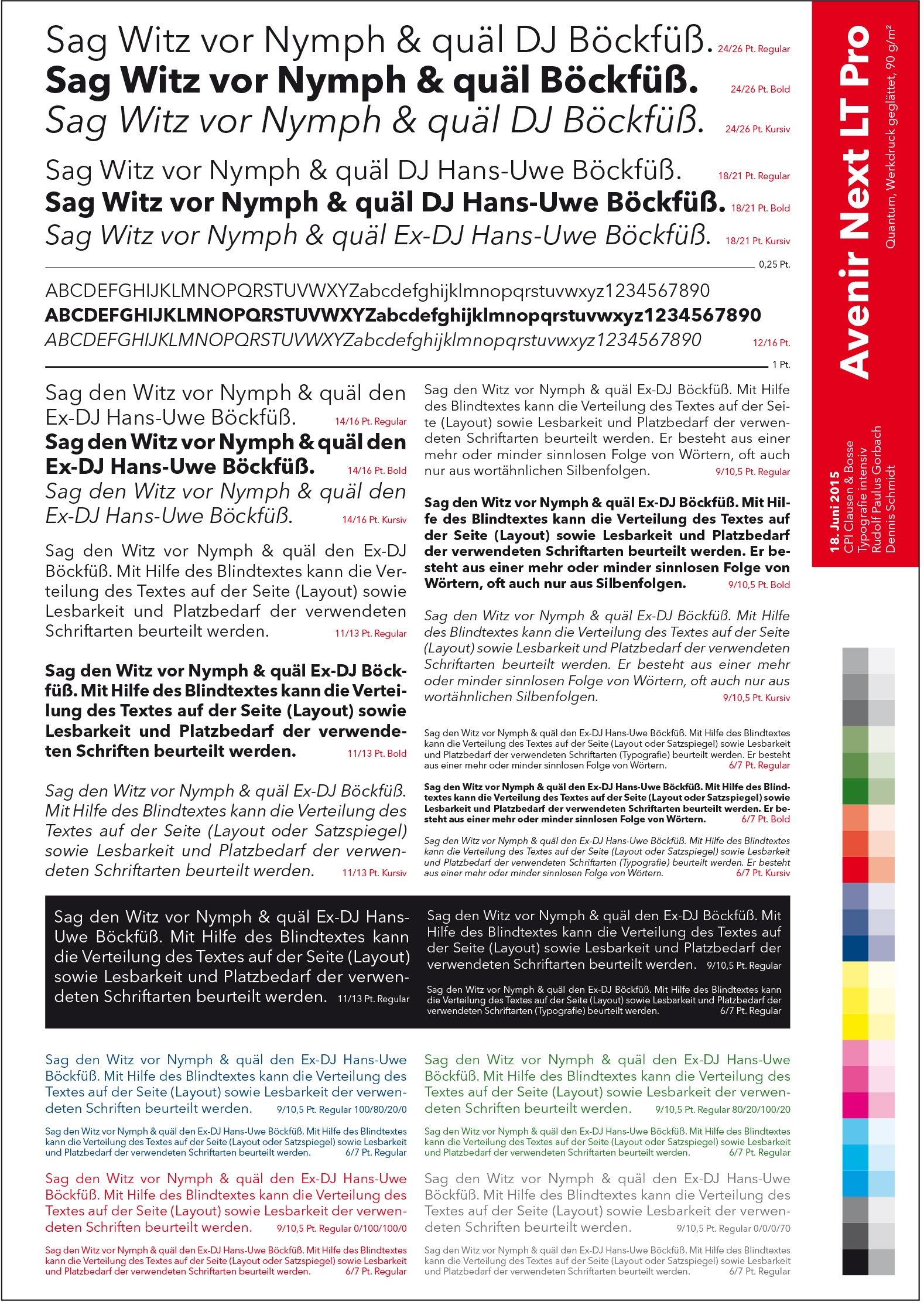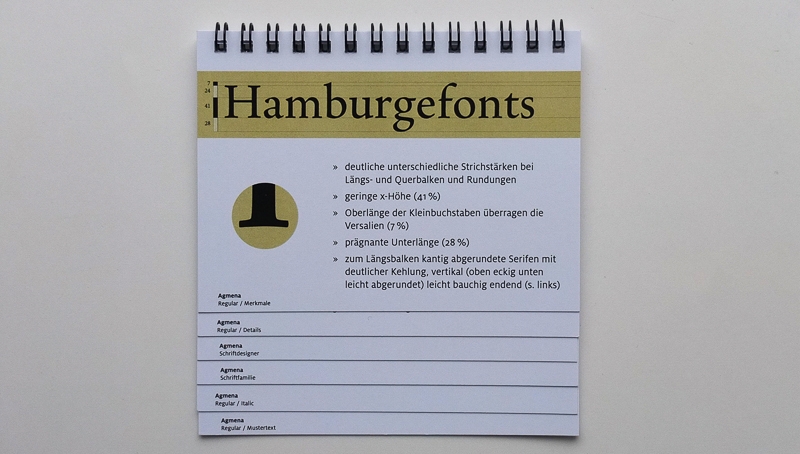
Studien zur Typografie
Praxis und Theorie kommen sich in der heutigen Aus- und Fortbildung immer näher. Deren Notwendigkeit ist vielleicht nicht so neu. Doch erweist sich gerade dies für »betonte« Praktiker sehr schnell bei der intensiven Beschäftigung mit einem Detailbereich aus der Gestaltung oder dem nachhaltigen »Studieren« eines Themas.
Im Seminar »Typografie intensiv« erhalten die Teilnehmerinnen und Teilnehmer vor dem Abschluss die Aufgabe, eine Studie zu einem typografie- und gestaltungsrelevanten Thema zu erarbeiten. Das Thema wird selbst gewählt und reicht – sehr bunt – in viele verschiedene Bereiche.
So findet man Betrachtungen zu geschichtlichen Themen der Typografie neben Untersuchungen heutiger Tendenzen in Teilbereichen, sehr persönliche Entwicklungsdarstellungen von Buchreihen, aber auch richtige Forschungsansätze. Die Studien müssen nicht zwangsläufig daraus Folgerungen empfehlen, können auch den Ist-Zustand beschreiben. Und nicht wenige Studien wurden in der späteren praktischen Arbeit der Teilnehmer weiter verfolgt.
Einige Beispiele, die direkt mit Typografie zu tun haben, möchte ich hier vorstellen. Manchmal ist es ja hilfreich, wenn man weiss, dass es solche Ansätze bereits gibt.
Dennis Schmid hat 2015 die Darstellung von 16 Druckschriften im Digitaldruck auf verschiedenen Papiersorten untersucht. Die Druckeignung wurde mit dem Offsetdruck verglichen. Die Studie zeichnet sich durch akribische Mikroskopaufnahmen aus, die zunächst im Bereich des Digitaldrucks verstörend aussehen. Doch in der Originalgröße der Schrift kommen die meisten Schrifttypen gut weg. Die Druckerei Clausen & Bosse (CPI books, Leck) war hierbei großzügiger Partner, indem sie Andrucke lieferte und die Studie selbst im Digitaldruck auf einer Quantum und Quantum Colour druckte und in einer Voraussage zur Verfügung stellte. Eine Ausgabe mit allen 16 Schriften auf verschiedenen Papiersorten ist bei CPI in Vorbereitung. Kontakt: dennis_ps@web.de
Abb. Testbögen für die Wirkung von Schriften im Digitaldruck
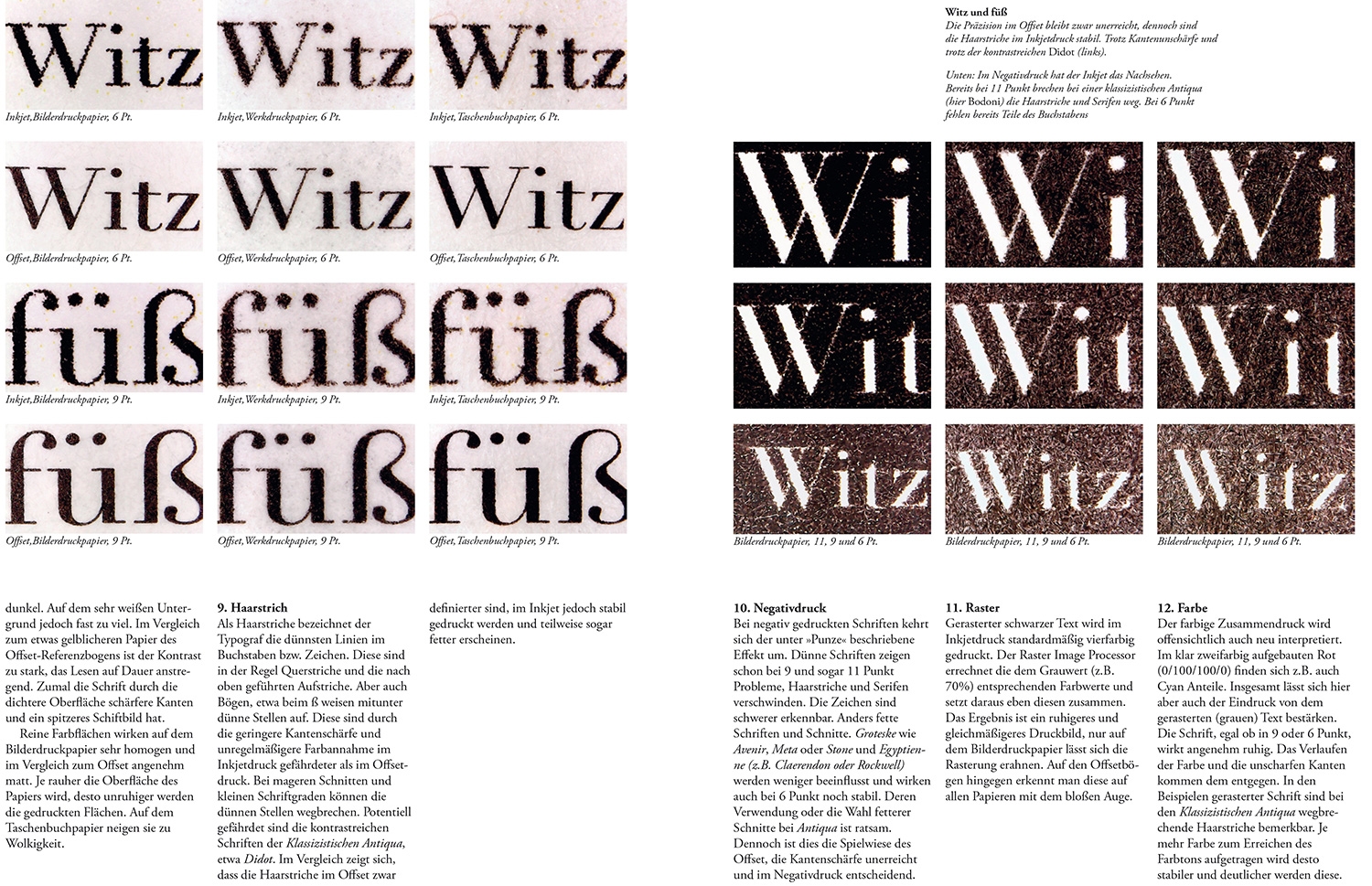
Abb. Schriftwiedergabe der Didot
Jeden Tag kommen neue serifenlosen Schriften heraus. Ich erinnerte mich an einen Vortrag von Hans-Peter Willberg bei der Herstellertagung in Irrsee 1986, wo er neue Textschriften vorstellte, die im Fotosatz oder bereits digital ohne direkte historische Vorbilder entstanden waren. Das gab für Manuel Kreuzer 2011 den Anlass, 21 neue serifenlosen Schriften der letzten 20 Jahre zu untersuchen. Die Auswahl war schwierig, denn bei der ersten Sammlung neuerer serifenlosen Schriften kamen bereits über 140 ernstzunehmende Schriften zusammen. Die Studie untersucht jeweils sehr genau die einzelnen Buchstaben der Schriften. Und damit lassen sich die Schriften im Detail gut vergleichen. Diese Arbeit ist danach im August Dreesbach Verlag erschienen.
Abb. Beispielseiten aus »20+1 – Vergleich von ausgewählten serifenlosen Schriften der letzten zwanzig Jahre« von Manuel Kreuzer
Untersuchungen und Anwendungen zur Mikrotypografie spielen im Seminar »Typografie intensiv« eine wichtige Rolle. Eine umfassende und sehr genaue Studie zur Manipulierbarkeit von Textschriften im mikrotypografischen Umfeld erarbeitete Catherine Avak 2009. Hierbei wurde anhand der Textschriften Fleischmann, Bodoni, Sabon, Syntax und Cecilia systematisch Laufweite, Kerning, Silbentrennung und der Wort- und Zeichenabstand verändert und in Beispielen gezeigt. Die für die jeweilige Schrift ideale Kombination wurde als Schlussfolgerung vorgestellt. avak@tgm-online.de
Abb. Ergebnis-Zusammenstellung bei der Schrift Fleischmann
Annett Riechert untersuchte 2015 das kleine g und wie es harmonisch in das jeweilige ganze Alphabet stilistisch eingebettet ist. Fragestellung war, ob das kleine g für unterschiedliche Anwendungsbereiche wie Mode, Nahrungsmittel, Zeitschrift typisch sein könnte.
Zunächst wurde die Geschichte des kleinen gs untersucht und seine Besonderheiten hervorgestellt. Mit Testpersonen wurden die Anwendungsbereiche untersucht. Das mag alles etwas fantastisch klingen, ist aber eine in sich plausible Studie. Natürlich ist hier trotz 35 Testpersonen das Ergebnis noch etwas offen. Aber Annett Riechers Arbeit sicher weiter daran. annett-riechert-design.de
Abb. Beispielseiten aus der Studie zum kleinen g
Jutta Fischer nahm sich 2013 neue Serifenschriften vor, wählte zehn aus: Milo, Arno Pro, Parango, Miller Text, Sierra, Ashbury, Expo Serie, Karina, Tundra und Agmena. Dabei wurden diese Schriften in einer eher spielerischen Form gezeigt. Jede Schrift bekam ein einzelnes kleines Booklet, in dem Merkmale und Details angeführt wurden. Der jeweilige Schriftdesigner wird knapp vorgestellt, die Schriftfamilie wird gezeigt und schließlich gibt es einen vergleichbaren Textabschnitt, der aus der 10/12 Punkt Regulär gesetzt ist. Das Ganze kann Ideen zur Verwendung einer neuen Schrift geben (ich selbst habe mich bereits anregen lassen mit der Verwendung der Agmena). info@going2web.de
Abb. Studie über neue Serifenschriften
Soeben ist eine Studie von Nicole Heinen fertig geworden mit dem Thema »Schriftwahl im Coachingkontext«. Anhand einzelner Worte wurde ein Ergebnis präsentiert zwischen
- Coach / Gestalter mit seinen Erfahrungen und Weltbild
- Klient / Betrachter mit seinen Erfahrungen und Weltbild
- Schriftklassen mit ihren Charaktereigenschaften
- Worte mit ihrer Information und Bedeutung
- Farben mit ihrer Schwingungsfrequenz und Wirkung.
Das jeweilige Wort wurde in der dafür passendsten Schrift ausgewählt.
Es könnten »schöpferische Schritte zu einem neuen Verständnis« entstehen die das Tor zu neuen Handlungsweisen öffnen«, schreibt die Autorin abschließend.
Abb. Seiten aus der Studie zur Schriftwahl im Coachingkontext